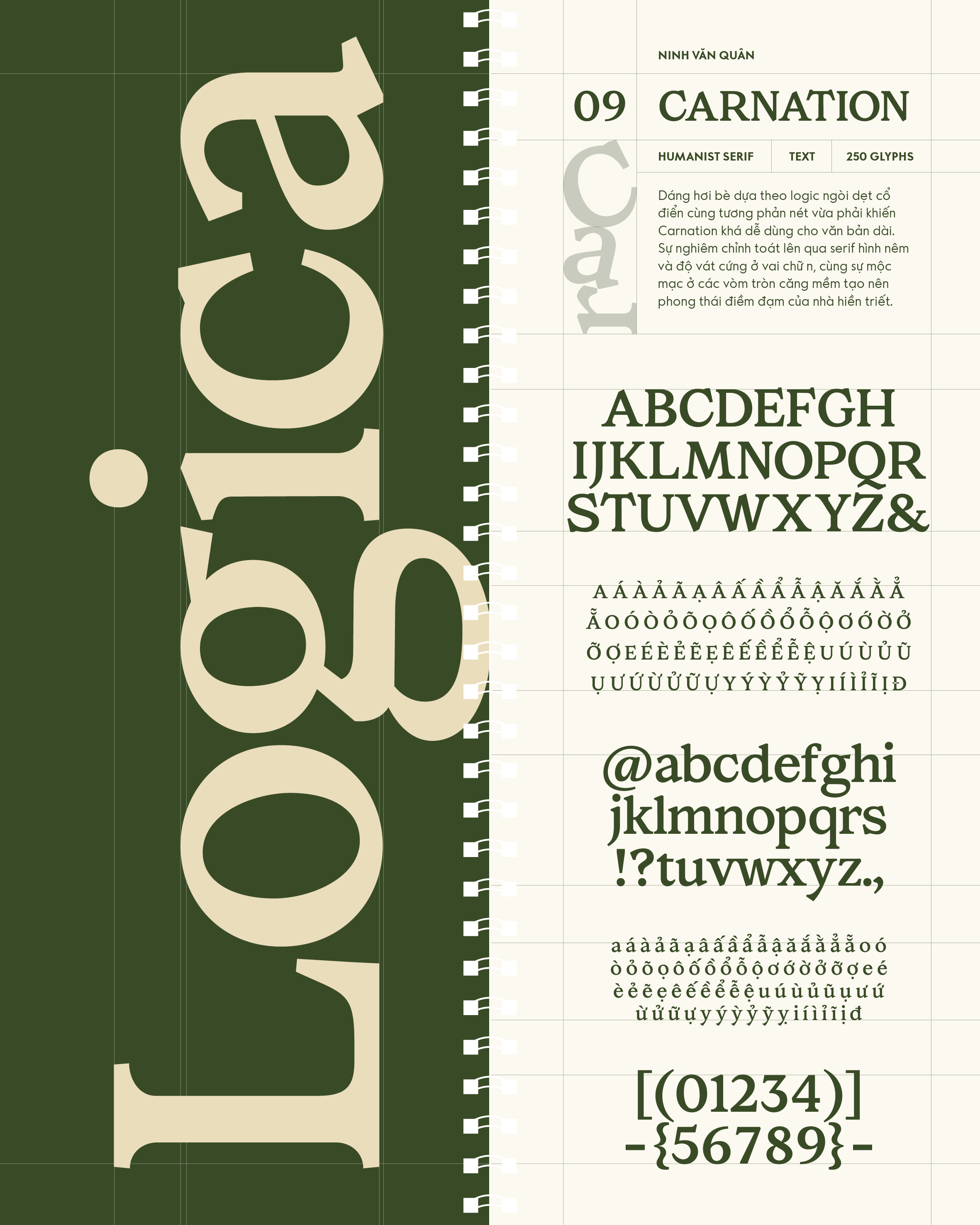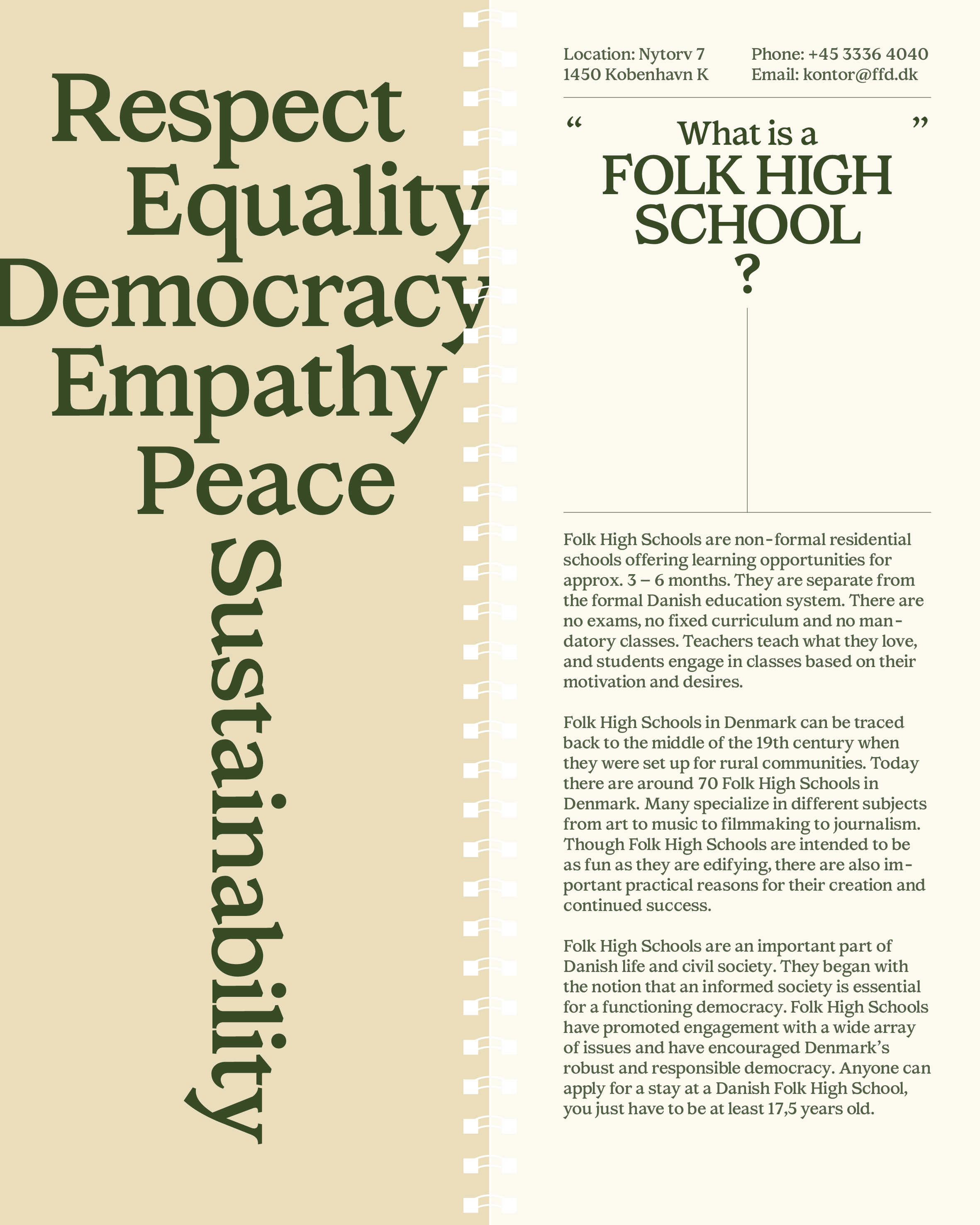
Carnation
Về Carnation: Dáng hơi bè dựa theo logic ngòi dẹt cổ điển cùng tương phản nét vừa phải khiến Carnation khá dễ dùng cho văn bản dài. Sự nghiêm chỉnh toát lên qua serif hình nêm và độ vát cứng ở vai chữ n, cùng sự mộc mạc ở các vòm tròn căng mềm tạo nên phong thái điềm đạm của nhà hiền triết.
Humanist Serif
Text
Ninh Văn Quân